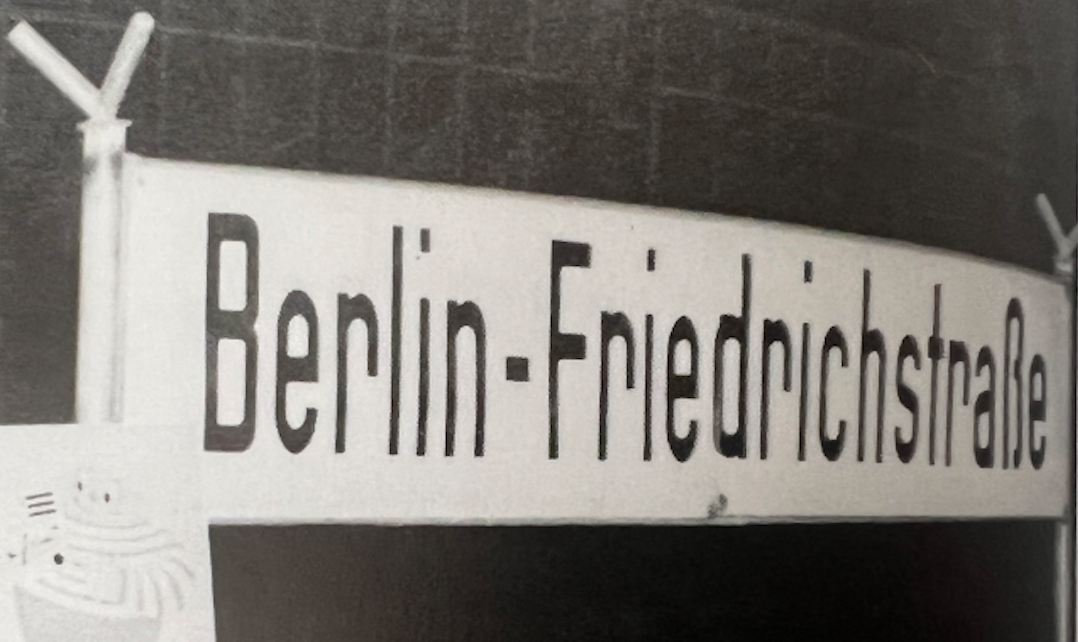
Stationsschild Berlin-Friedrichstraße DDR
ich bin dringend auf der Suche nach der Schrift der S-Bahn Haltestelle Friedrichstraße vor Maueröffnung.
Vor allem das kleine "r" ist sehr prägnant. Daher kann es nicht die Cst Berlin East, Berthold Akzidenz Grotesk, Din Eng und auch nicht die AT Erbar sein.
Hallo @Gansewein, es wird keine direkt auf deiner Vorlage basierende Satzschrift geben. Peter Wiegel – hier registriert als @catfonts – hat einige Schriften nach historischen (u. a. Berliner) Letterings und Schildern frei veröffentlicht, falls dir das irgendwie bei deiner dringenden Suche hilft.
Berliner Wand
Osterbar
Preußische Musterzeichnung IV 44 Ausgabe 3
Preußische Musterzeichnung VI 9 Auflage 2
Berlin Email
etc.
vielen Dank für das Feedback! Nach meiner weiteren Suche, ist mir aufgefallen, dass ich vor einigen Jahren, exakt diese Schrift in das Forum gestellt habe. Damals war die einzige Lösung selber Hand anzulegen. So wird es wieder sein, aber dieses Mal auf Grundlage der von D2C vorgeschlagenen Catfonts. Vielen Dank für die Tipps!